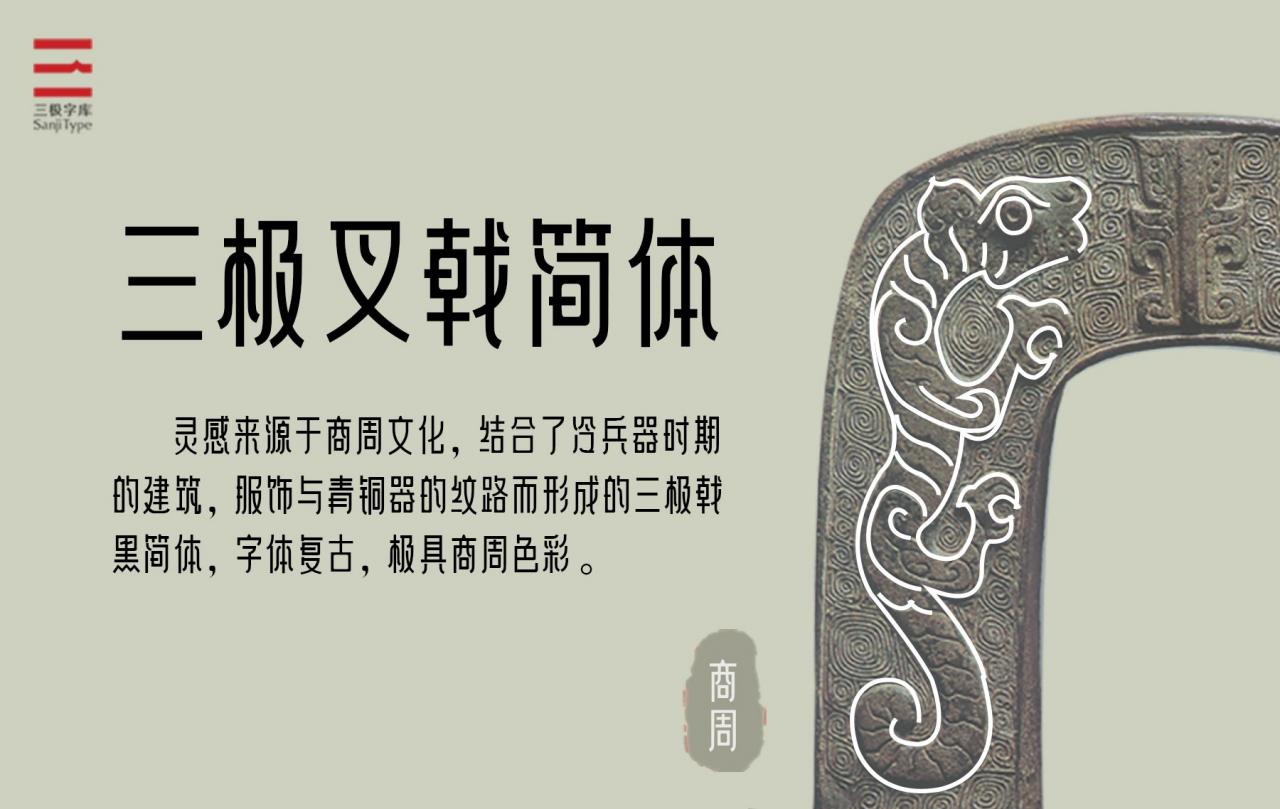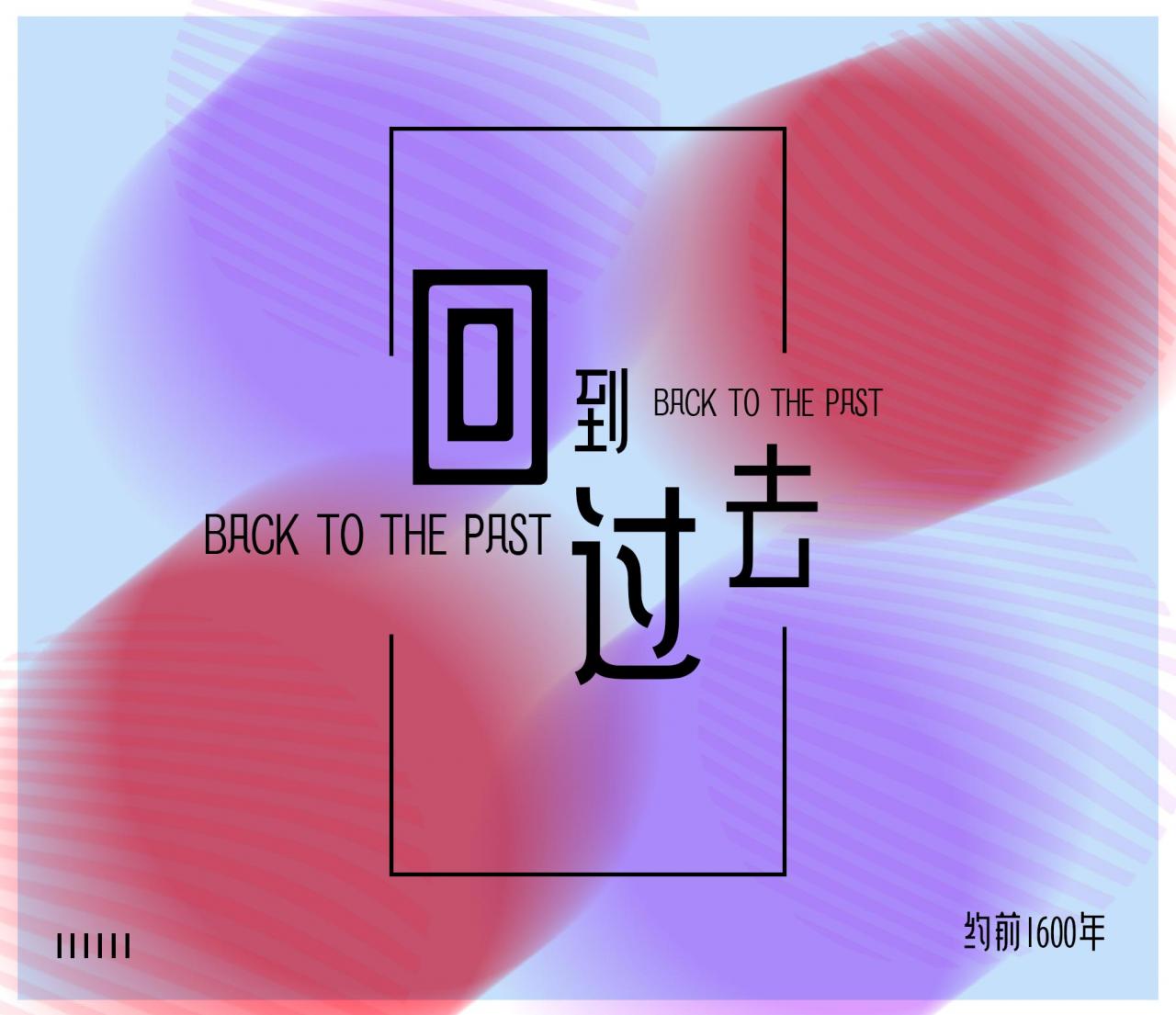
三极叉戟简体
字体名称:三极叉戟简体
设计师:蔡建文,曹陆迎
所属分类:黑体
三极叉戟简体灵感来源于商周文化,结合了冷兵器时期的建筑,服饰与青铜器的纹路而形成的三极戟黑简体,字体复古,极具商周色彩。适用于个性海报设计,复古风格包装设计等。
适用媒介:杂志、书籍、广告、标志、宣传册、包装、影视、动漫、交互设计